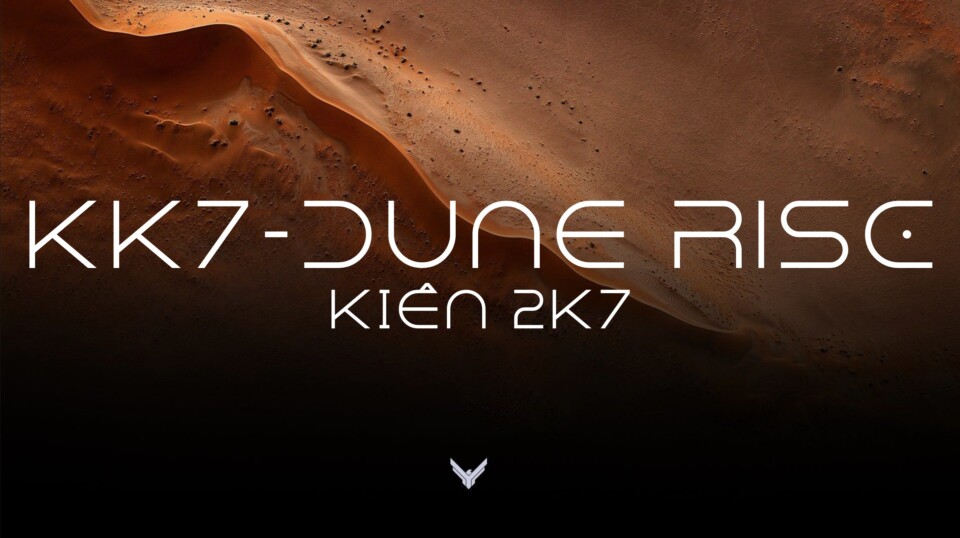
Giới thiệu về Font Việt Hóa KK7-Dune Rise
Trong thế giới đồ họa hiện đại, việc lựa chọn Font Chữ phù hợp đóng vai trò quan trọng để truyền tải thông điệp nghệ thuật. Font Việt Hóa KK7-Dune Rise là một bộ phông chữ độc đáo, lấy cảm hứng từ phong cách tương lai và các bộ phim khoa học viễn tưởng đình đám. Với các đường nét sắc sảo, tối giản nhưng vô cùng mạnh mẽ, bộ font này đã được tinh chỉnh kỹ lưỡng để hỗ trợ đầy đủ tiếng Việt, giúp người dùng dễ dàng ứng dụng vào các dự án thiết kế mà không lo lỗi hiển thị. Đây là lựa chọn lý tưởng cho những ai yêu thích sự phá cách và hiện đại.
Đặc điểm nổi bật của bộ Font Việt Hóa KK7-Dune Rise
Thiết kế mang hơi thở tương lai
Điểm nhấn lớn nhất của Font Việt Hóa KK7-Dune Rise chính là cấu trúc hình học vuông vức kết hợp cùng các khoảng hở tinh tế. Điều này tạo nên cảm giác không gian rộng mở và công nghệ cao, rất phù hợp cho các tiêu đề phim, bìa sách hoặc poster sự kiện công nghệ.
Khả năng ứng dụng đa dạng
Dù mang phong cách Futuristic, nhưng bộ phông này vẫn đảm bảo tính dễ đọc. Bạn có thể sử dụng nó để thiết kế logo, làm layout cho website hoặc tạo các ấn phẩm truyền thông cho trường học. Phiên bản Việt hóa giúp bạn tự do sáng tạo nội dung mà vẫn giữ được cái “chất” riêng biệt của bản gốc.
Để tận dụng tối đa vẻ đẹp của Font Việt Hóa KK7-Dune Rise, bạn nên kết hợp với các hiệu ứng ánh sáng neon hoặc gradient màu tối. Việc cài đặt vô cùng đơn giản, chỉ cần tải về và cài vào hệ thống là bạn đã có ngay một công cụ mạnh mẽ để nâng tầm tác phẩm của mình. Nếu bạn đang tìm kiếm những bộ Font Miễn Phí, Font Việt Hóa, Font Việt Hóa KK7-Dune Rise chất lượng, đừng bỏ qua cơ hội sở hữu siêu phẩm này để khẳng định phong cách thiết kế chuyên nghiệp của riêng mình ngay hôm nay.